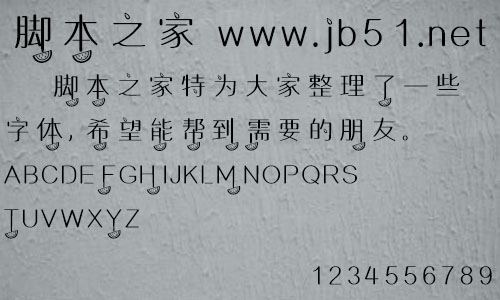
義啟你這個(gè)瓜娃子一款不錯(cuò)的藝術(shù)字體,由義啟字庫出品,字體筆觸粗細(xì)適中,字體中以西瓜圖案進(jìn)行點(diǎn)綴,看上去十分的不錯(cuò),適合應(yīng)用于藝術(shù)設(shè)計(jì)、平面宣傳設(shè)計(jì)、網(wǎng)頁設(shè)計(jì),書法字帖等領(lǐng)域,需要的朋友可以前來本站下載。